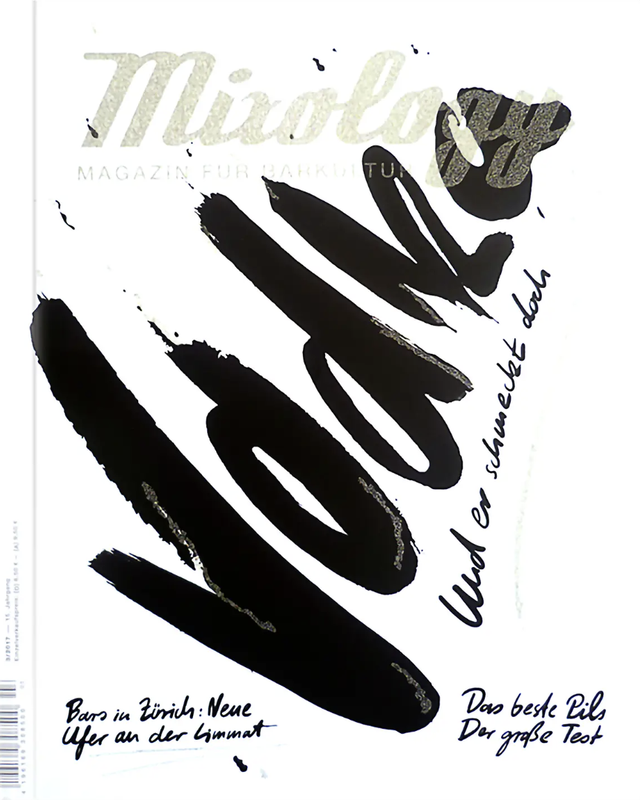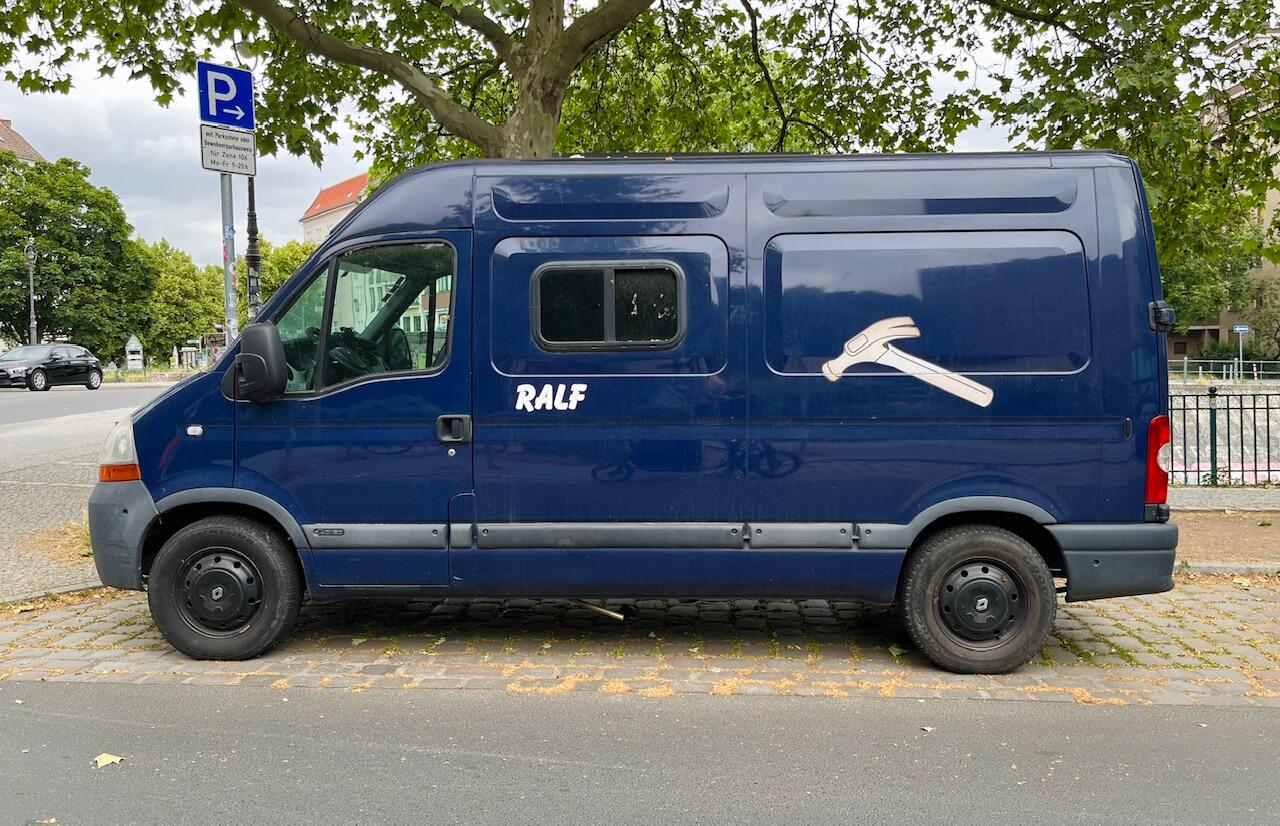
Nun ja, x und k haben eindeutig das in einigen gebrochenen Schriften verwendete Buxhstaben-Skelett, während an der Ausführung in der Tat nix gebrochen ist ... Deswegen "runde Gebrochene"!?
Ich würde da eher von einer Mischform sprechen. Ich habe irgendwann mal gehört, dass so etwas bei Handschriften in der ersten Hälfte des 20. Jahrhunderts durchaus vorkam. - Je nachdem ob Kurrent oder Antiqua gelernt worden war, stellten sich dann in Handschriften Mischformen ein. Und das interpretiere ich wie eine Mischform in einer Druckschrift.
Also ich lese da Shish … -o
…und im Jahr 2026 noch dazu mit Transparenzreduzierungs-Geisterlinien garniert. So ein shish!
»Mixology« konnte ich noch lesen, aber dann war ich auch bei »Shish« (meine Gedanken schweiften zwischen Shisha, Çiş und Çüş hin und her …).
Viel schlimmer finde ich die Farbgebung. Garantiert nicht »barriefrei«. Und ja, die Geisterlinien hätte man bemerken können.
Dieses typografische Fundstück (Hauptbahnhof München) ist zugleich auch ein Bilderrätsel.
Ich habe keine Ahnung, für was das »F« steht. Any ideas?
Die offensichtlich komplett überforderte KI hat Folgendes ausgespuckt:
– Frauenbereich
– Fehlwurf
– Flughafen oder Fahrzeugreinigung
– Hersteller Firma Föhrenbach
– Abfallsack »Typ F« (Lieblingsantwort)